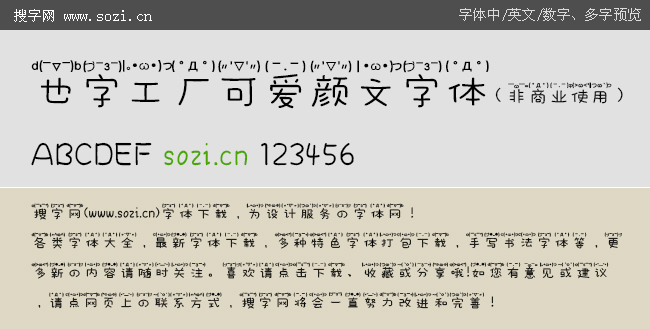
也字工廠可愛顏文字體
搜字網(wǎng)給大家提供一款也字工廠可愛顏文字體(非商業(yè)使用)中文字體下載,也字工廠可愛顏文字體是一款卡通字體,字體是可愛的書寫風(fēng)格,非?蓯塾腥ぃ煮w上面裝飾了顏文字。適合應(yīng)用于兒童海報(bào)、網(wǎng)頁設(shè)計(jì)等應(yīng)用(此字體為個人非商用版,商用可以聯(lián)系:官方網(wǎng)址:https://yefont.com/home,聯(lián)系方式:13798980448)。